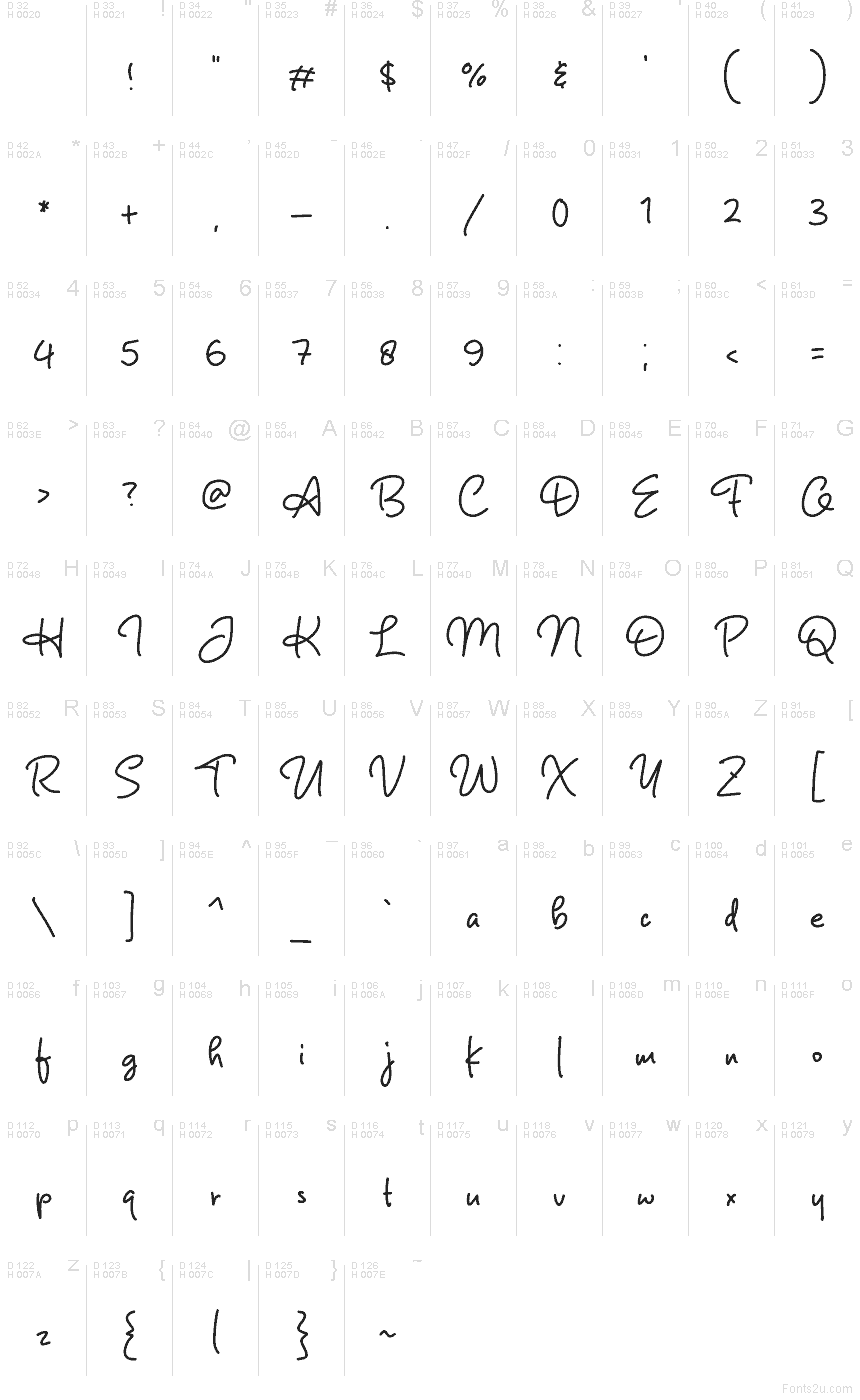
Hunter Script
Hunter Script od MJType je bezplatné ručne písané písmo s voľnými spojenými ťahmi a výraznými slučkami pri veľkých písmenách, ktoré dodávajú nápisom osobný, kaligrafický rytmus. Tvary zostávajú zaoblené a otvorené, s jednoduchými malými písmenami, vďaka ktorým text plynie prirodzene a bez zbytočných ozdôb.
Hunter Script sa skvele hodí pre logá, citáty, blahoželania, pozvánky, obaly či branding v štýle podpisu, pretože pôsobí autenticky a nie je zbytočne komplikované. Toto bezplatné písmo je tiež ideálne na grafiku pre sociálne siete a krátke texty, ak hľadáte neformálny, priateľský a priamy vizuál.